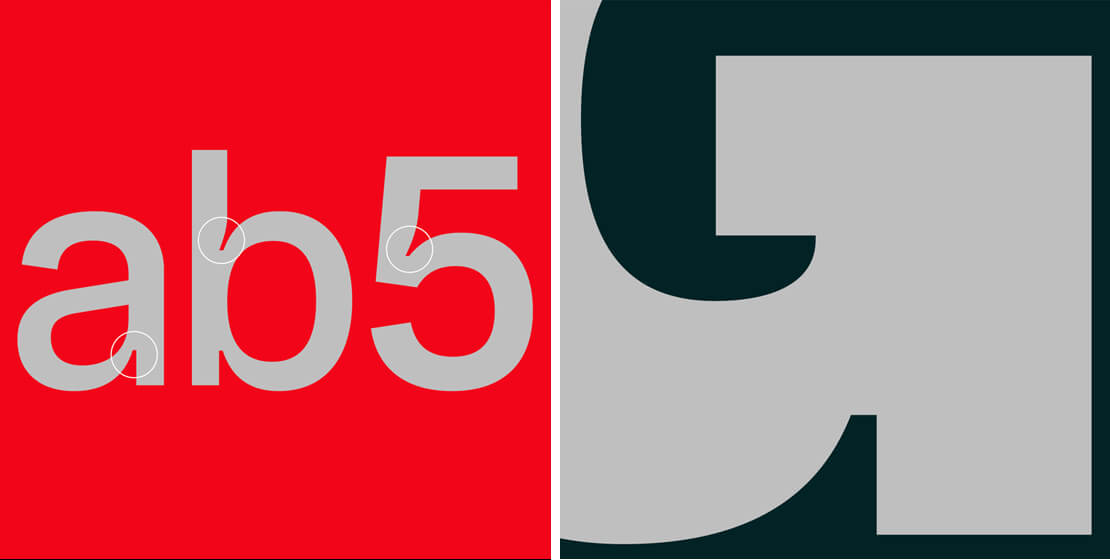
Schriftfamilie »Heltar« bei The Northern Block erschienen
»Heltar« ist sowohl eine Hommage an die Vergangenheit als auch eine Vision für die Zukunft. Die 16 Schnitte umfassende Schriftfamilie ist neu bei The Northern Block erschienen.
Der Name Heltar ist bewusst gewählt und leitet sich von „Hel“ in „Helvetica“ ab. Doch Heltar versteht sich nicht nur als Hommage, sondern vielmehr als Weiterentwicklung. Schriftdesigner Jonathan Hill war sich der Herausforderung bewusst, dass es bereits zahlreiche Alternativen zur Helvetica gibt. Genau diese Herausforderung stand im Mittelpunkt seiner Gestaltung der neuen Schriftfamilie.
Hill wollte eine Schrift schaffen, die Helvetica würdigt und gleichzeitig etwas völlig Eigenes darstellt. Eine Schrift für das Hier und Jetzt – und für die Benutzeroberflächen von morgen. Die zentrale Frage bei der Gestaltung von Heltar lautete also: „Wie kann man die Groteskschrift neu interpretieren?“ Um diese Frage zu beantworten, begann Jonathan Hill von Grund auf neu. Nach etwa neun Wochen intensiver Arbeit erweckte er die Schrift schließlich zum Leben.
Heltar ist eine moderne neo-groteske Schrift, die acht Gewichte mit passenden „Obliques“ umfasst und über 650 Zeichen pro Stil bietet. Sie enthält verschiedene Zahlenvariationen, alternative Zeichen sowie spezielle Glyphen wie Pfeile, nummerierte Kreise oder Quadrate. Zudem bietet Heltar eine umfassende Sprachunterstützung für West-, Süd- und Mitteleuropa.